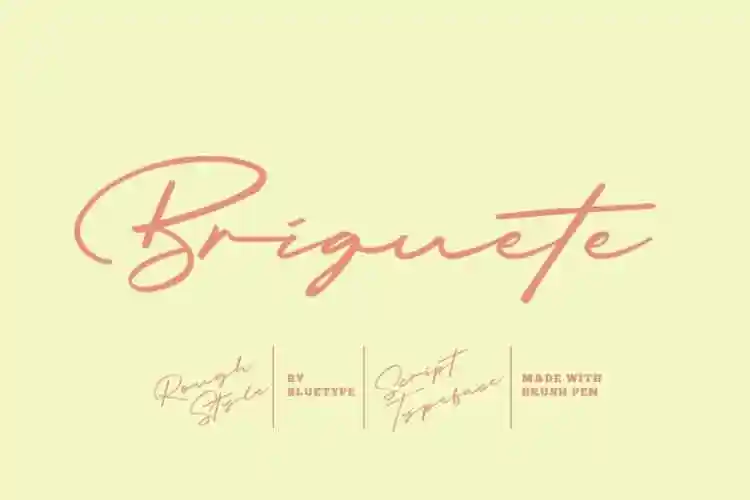
Briquete Handwritten Font – Fonte Grátis
Briquete Handwritten Font
Esta fonte é uma elegante tipografia de script natural criada por Bluetype, que oferece suporte a feições OpenType. Ela inclui numerais, pontuação e é altamente adaptável para múltiplas línguas, tornando-a versátil para um amplo espectro de projetos gráficos. Suavemente natural e perfeitamente humana, esta fonte foi elaborada usando uma pena a mão. Seus traços fluidos e suas nuances são perfeitos para aplicar em vários contextos, desde criação de marca e design para casamentos até embalagens de produtos e designs de produto. Além disso, ela é uma excelente escolha para anúncios, etiquetas, fotografia e convites. Com sua simplicidade sofisticada e capacidades extensas, esta fonte oferece uma ferramenta poderosa para os designers que buscam um estilo único e autêntico. Engajante e versátil, a Briquete Handwritten Font é um recurso indispensável para qualquer designer em busca de uma solução perfeita para o seu projeto.